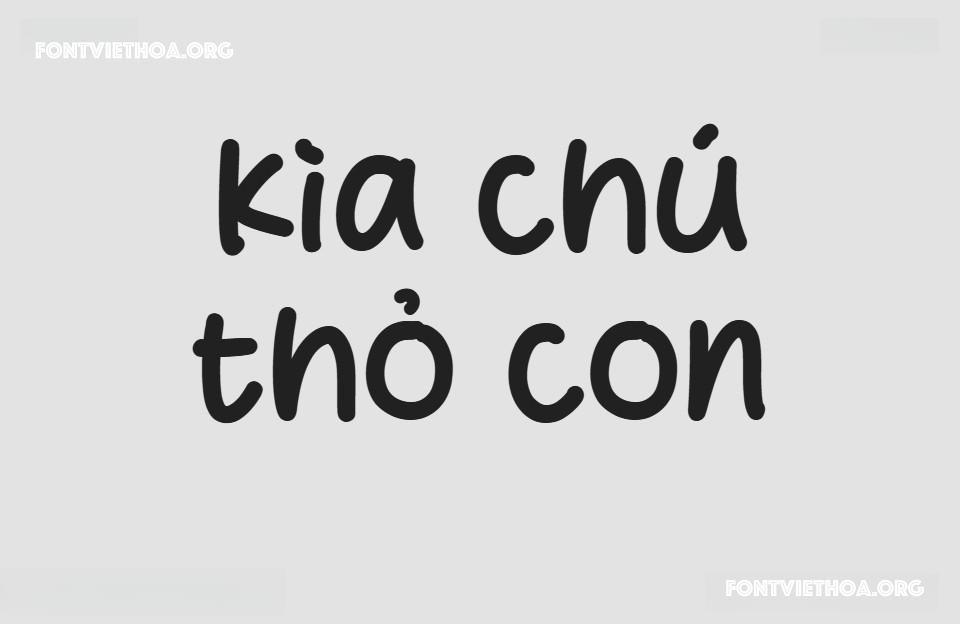
Tên font: Font Việt hoá Welcome Darling
Font Việt hoá Welcome Darling là một font chữ viết tay rất dễ thương, với thiết kế bo tròn, tạo nên sự thân thiện và gần gũi. Font này rất phù hợp với các thiết kế về trẻ em hoặc tiệm bánh, nơi cần tạo ra không khí vui vẻ và ấm áp.
Font Welcome Darling có nhiều đặc điểm nổi bật, bao gồm: